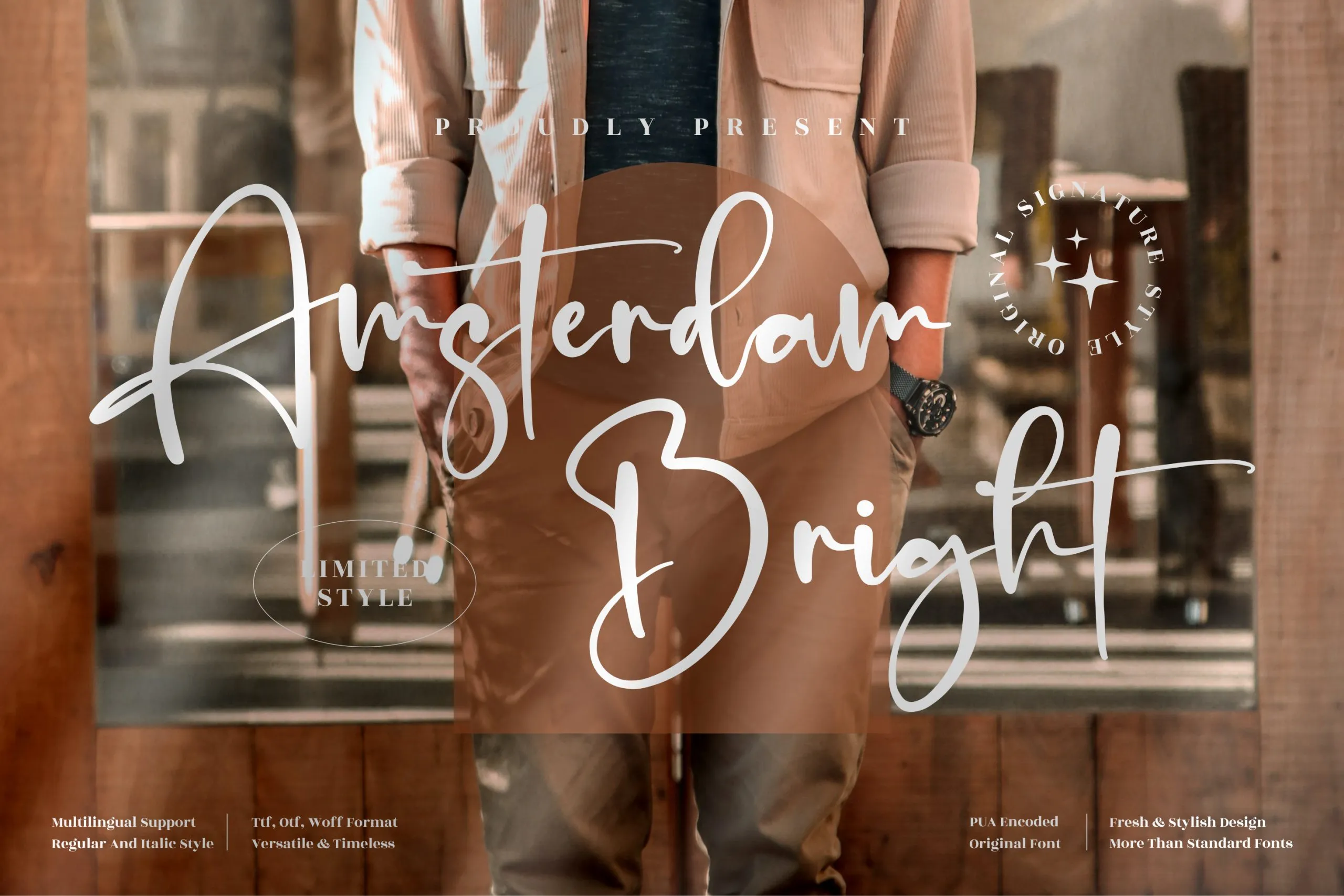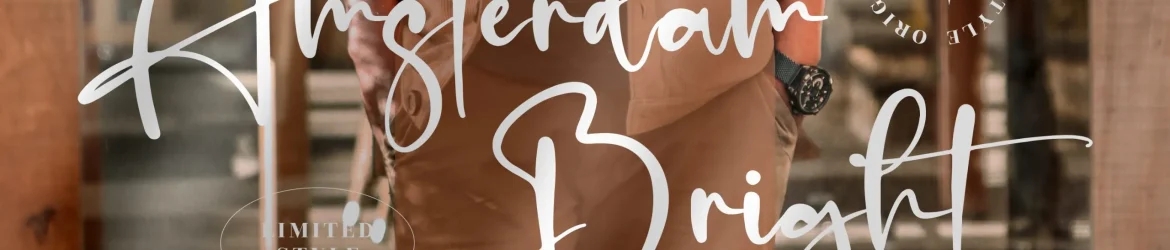
Amsterdam Bright Font é uma elegante tipografia ideal para aqueles que buscam um toque sofisticado no design. De designer perspectype, esta é uma fonte premium perfeitamente adaptável a diversos tipos de projetos, desde logotipos e identidades empresariais até invitations e embalagens de produtos. Suas linhas fluidas e detalhes precisos tornam-a uma opção excepcional para qualquer projeto que deseje um brilho único e um toque de sofisticação. Ideal para design de móveis, pacotes de produto, itens personalizados, cartões de presente e embalagens de livro, esta fonte irá transformar suas criações em algo especial. Não importa qual seja seu próximo projeto, Amsterdam Bright está aqui para garantir um toque autêntico que enriquece seu design.